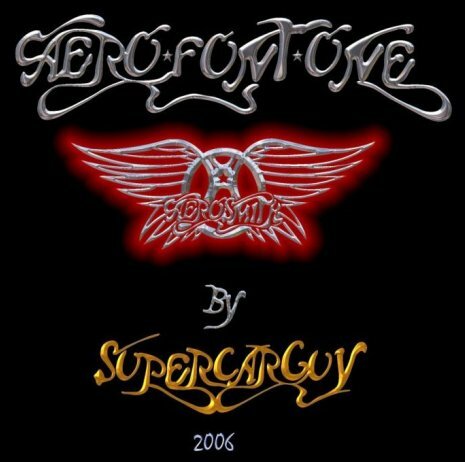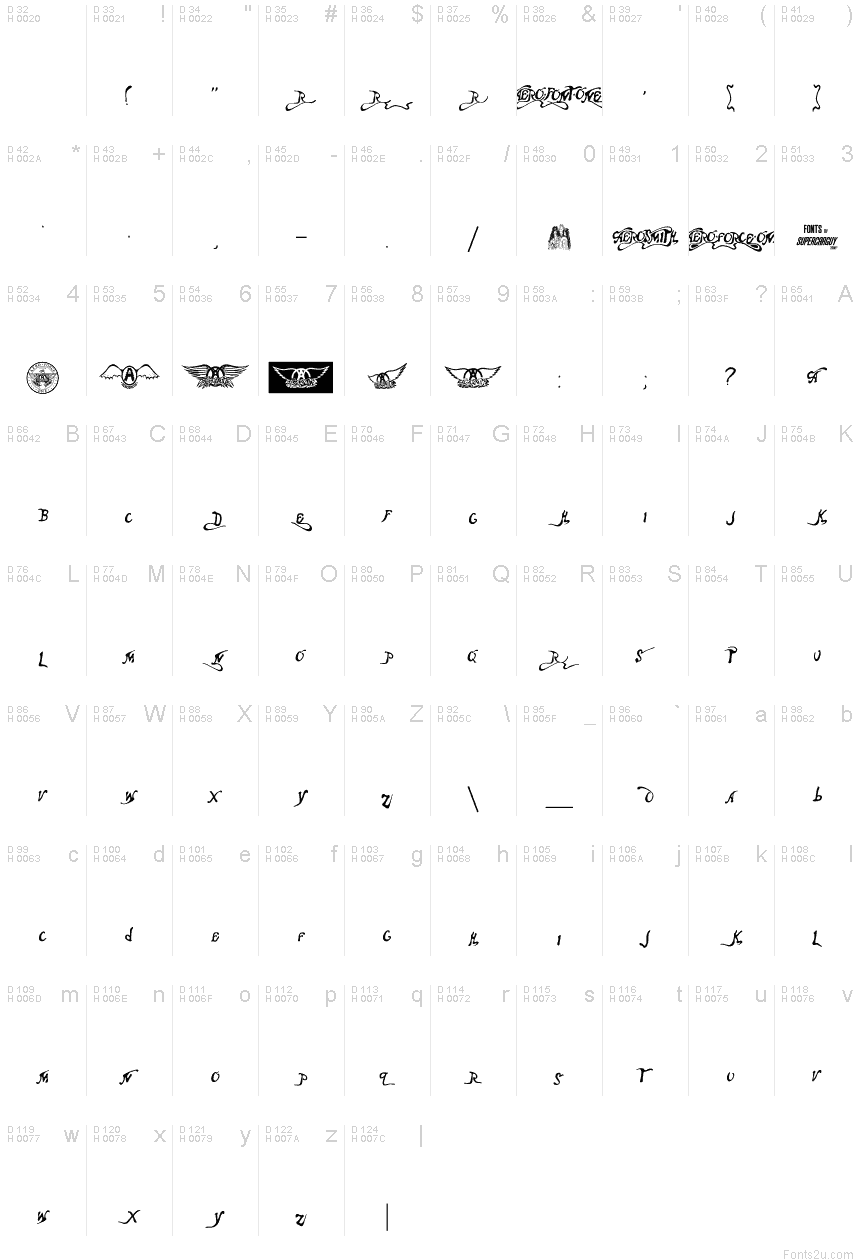
Aero Font One od Supercarguy to darmowy, zniekształcony krój displayowy, który wygląda, jakby został naniesiony na stronę energicznym pociągnięciem pędzla. Litery wyginają się i nachodzą na siebie, tworząc atramentowe, „wietrzne” pociągnięcia, które balansują między kaligrafią a graffiti. Mimo płynnych kształtów krój pozostaje zaskakująco czytelny, zapewniając dziki, pełen energii wyraz bez utraty komunikatu.
Jako darmowy font, Aero Font One świetnie sprawdza się w logo zespołów, plakatach koncertowych, okładkach książek fantasy, brandingu streetwearowym, tytułach gier i wyrazistych ulotkach eventowych. Gęste, czarne kształty przyciągają uwagę w większym rozmiarze, gdzie pełne rozmachu krzywe i zawijasy mogą w pełni wybrzmieć. W przypadku mniejszych tekstów warto zestawić go z czystym, wąskim krojem bezszeryfowym, aby zrównoważyć jego turbulentny, odręcznie rysowany charakter.
Aero Font One — Prezentacja czcionki